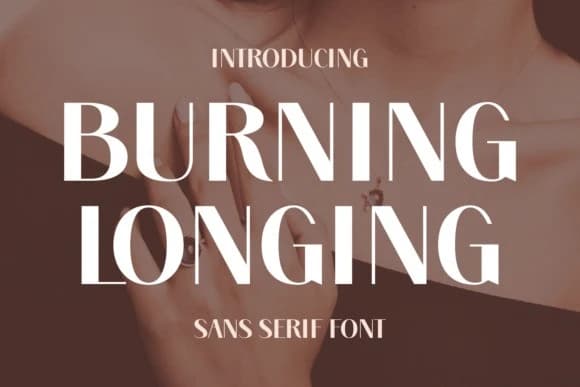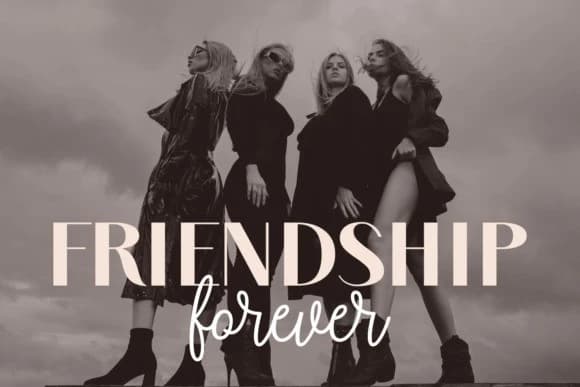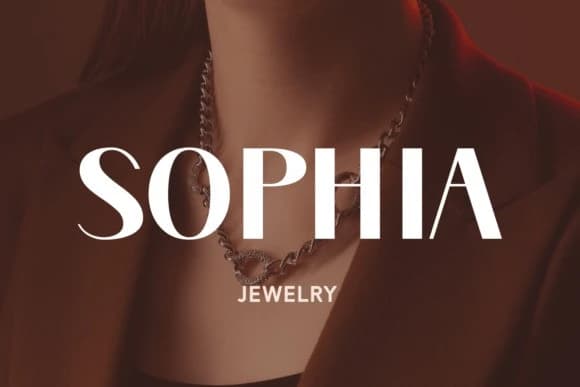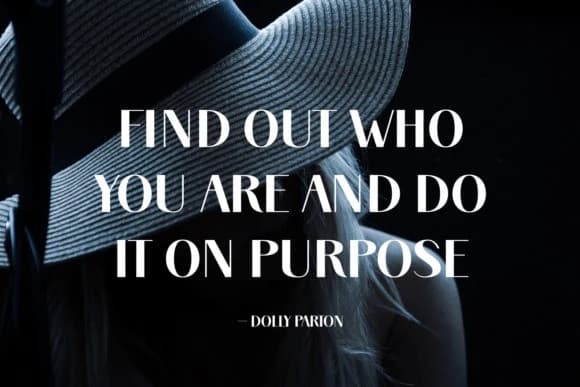
Burning Longing Font
Burning Longing Font, cesur ve kendinden emin bir sans-serif fontudur. Konu ne olursa olsun, bu font fontlarınızın kütüphanesine inanılmaz bir katkı sağlayacaktır, çünkü her türlü yaratımı yükseltebilme potansiyeline sahiptir.